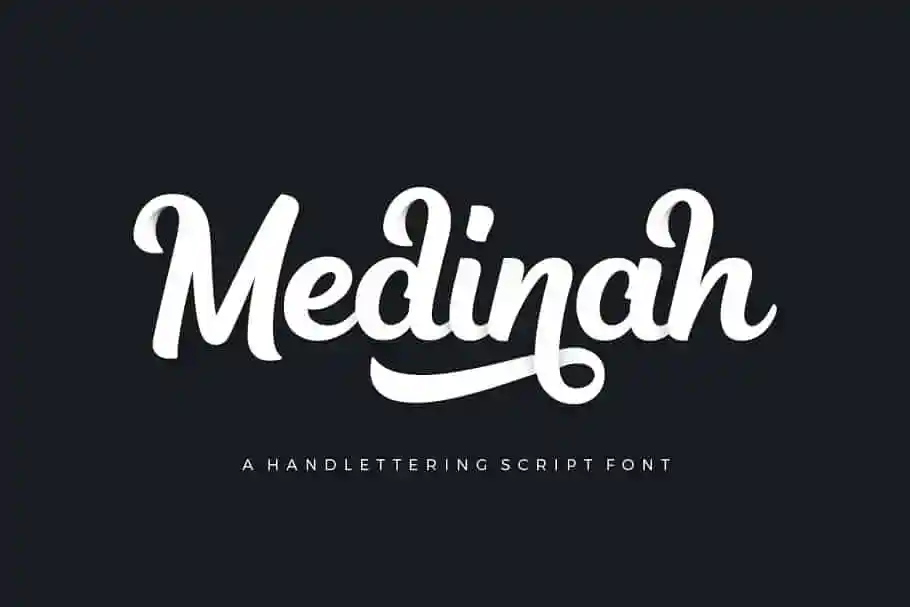
Na categoria dos fonts Script para designers atentos à qualidade, apresentamos a Medinah Font. Desenvolvida por zziplex, essa elegante mão-dura script é perfeita para aquilo que busca um charme casual e irreverente. Perfeito tanto para o logotipo quanto para letras de parede, cartazes, roupas, etiquetas, cabeçalhos de sites ou até mesmo etiquetas em pacotes, a Medinah é uma escolha óbvia para qualquer tipo de projeto criativo. Ideal para designers que buscam uma fonte suave e versátil para seus trabalhos, a Medinah se destaca por sua facilidade em adaptar-se a diferentes contextos. Seja um design de roupas, um site moderno ou até mesmo uma etiqueta personalizada, essa tipografia é capaz de trazer vida ao seu trabalho. Medinah é mais do que uma font: é um complemento indispensável para qualquer designer comprometido com criatividade e qualidade. Suave mas forte, ela promove a criação de um estilo único e autêntico em seus projetos. Experimente a Medinah e descubra como essa font pode transformar seu trabalho.